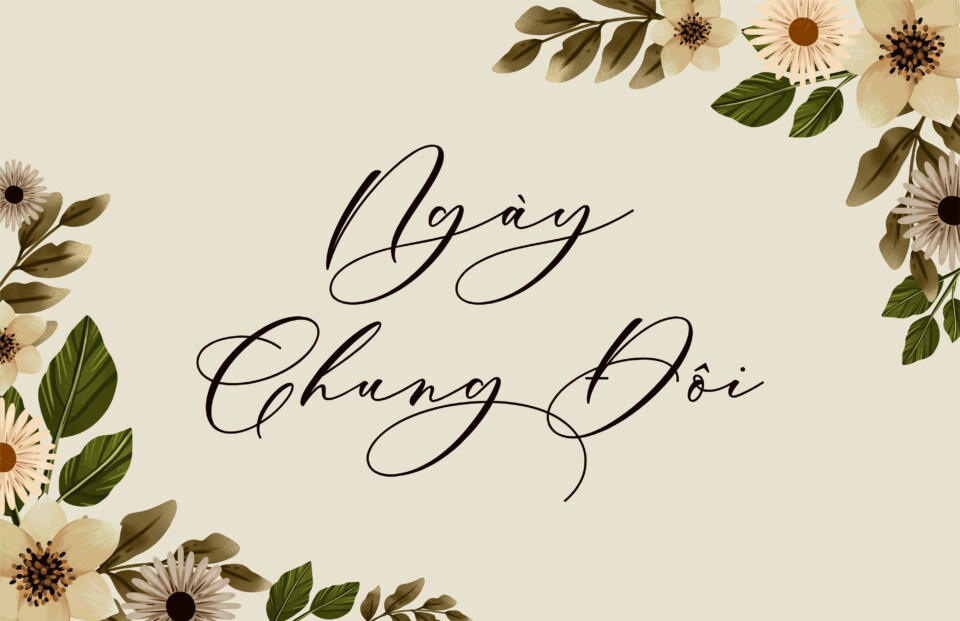
Giới thiệu về bộ Font Việt hóa VN Cathiy Betiey
Trong thế giới đồ họa hiện đại, việc lựa chọn một Font Chữ phù hợp đóng vai trò quan trọng trong việc truyền tải thông điệp và cảm xúc. Font Việt hóa VN Cathiy Betiey là một trong những bộ phông chữ thuộc phong cách Script hiện đại, mang đậm tính nghệ thuật và sự mềm mại. Với các đường nét uyển chuyển, bộ font này cực kỳ phù hợp cho những dự án thiết kế cần sự tinh tế, thanh lịch nhưng không kém phần trẻ trung.
Ưu điểm nổi bật của VN Cathiy Betiey
Điểm mạnh nhất của Font Việt hóa VN Cathiy Betiey chính là khả năng hiển thị tiếng Việt hoàn hảo, không bị lỗi dấu hay sai lệch khoảng cách giữa các ký tự. Điều này giúp các nhà thiết kế tại Việt Nam tiết kiệm thời gian chỉnh sửa thủ công. Các đường nét thanh mảnh kết hợp cùng những vòng xoắn điệu đà tạo nên một tổng thể hài hòa, giúp sản phẩm trở nên thu hút và chuyên nghiệp hơn trong mắt người xem.
Ứng dụng Font Việt hóa VN Cathiy Betiey trong thực tế
Bộ font này được ứng dụng rộng rãi trong nhiều lĩnh vực khác nhau, đặc biệt là trong môi trường học đường và trang trí sự kiện. Học sinh có thể sử dụng font để trình bày các bài thuyết trình, làm thiệp chúc mừng thầy cô hoặc trang trí bìa báo tường. Ngoài ra, VN Cathiy Betiey còn là lựa chọn hàng đầu cho các thiết kế thiệp cưới, nhãn hàng mỹ phẩm, hoặc các ấn phẩm truyền thông trên mạng xã hội nhờ vẻ ngoài nữ tính và sang trọng.
Kết luận về bộ font chất lượng